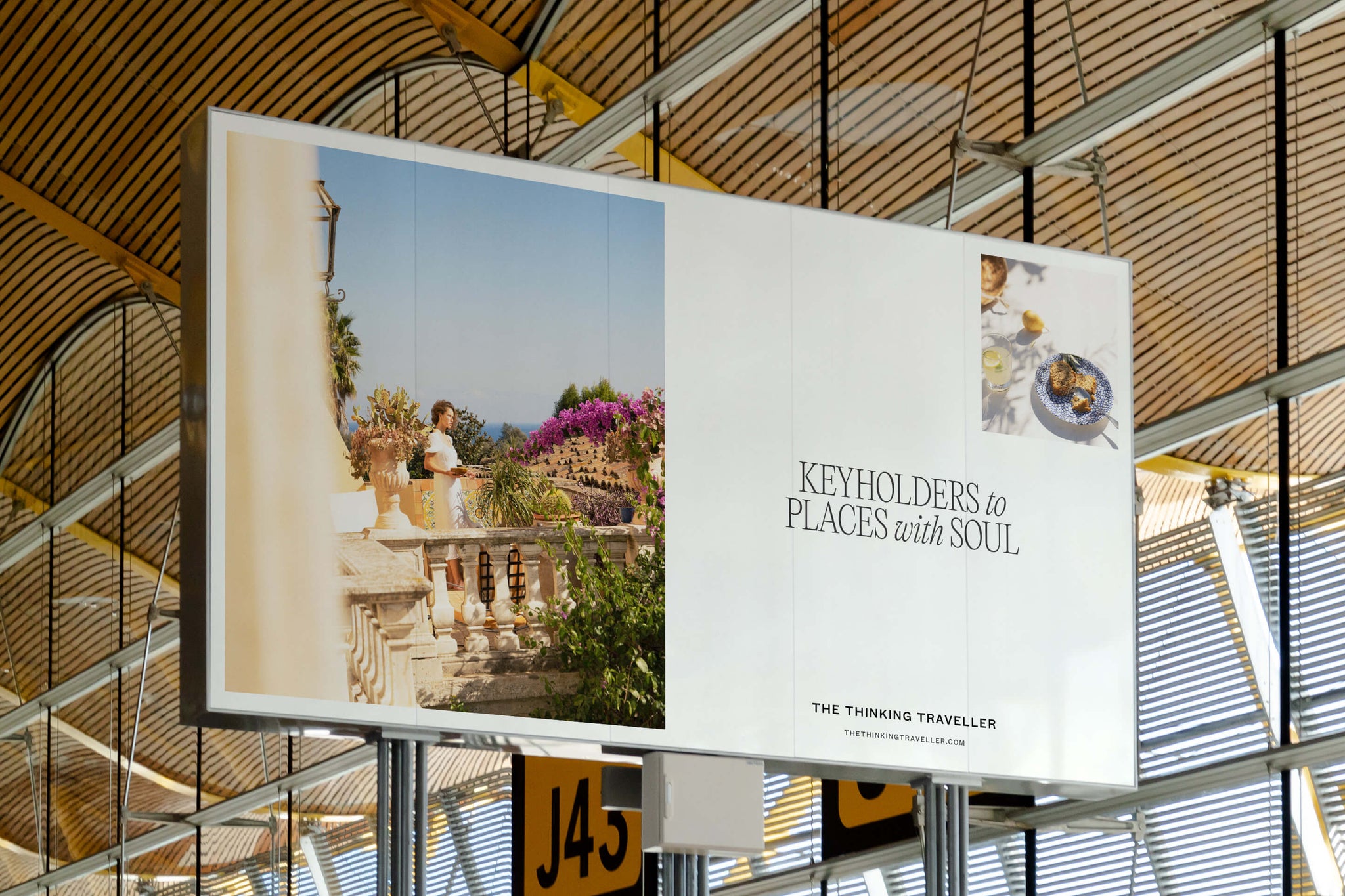
Depuis vingt ans, The Thinking Traveller rend les vacances en villa plus réfléchies.
Mais à mesure que le marché de la recherche de villas s'est développé, la marque s'est perdue dans un océan de piscines à débordement. Dans un marché de plus en plus générique et fonctionnel, pour inspirer le voyageur de luxe de demain, il lui fallait une marque qui prône l'originalité.
PARTAGER L'EXTRAORDINAIRE
Contrairement à ses concurrents, The Thinking Traveller propose ses maisons de caractère exclusivement par son intermédiaire. Grâce à leur connaissance approfondie de ces lieux, les équipes locales talentueuses peuvent créer des vacances uniques et sur mesure. Une identité de marque était donc nécessaire pour mettre en valeur cette expertise. Afin de repositionner The Thinking Traveller, non plus comme une agence de location de villas, mais comme un « détenteur de clés de lieux ayant une âme », nous avons commencé par décrire ces lieux exceptionnels dans un langage bien éloigné du jargon immobilier des « villas exclusives ».
PASSIONNÉ PAR LES LIAISONS HUMAINES
Mettre en œuvre une nouvelle image de marque tout en gérant une plateforme de réservation primée n'est pas chose aisée. Nous avons travaillé en Narrowcollaboration avec l'équipe de développement interne de l'entreprise pour l'aider à concrétiser cette nouvelle vision, tout en assurant une transition fluide et en maintenant le rythme soutenu des réservations pour la saison à venir.
DES LIEUX QUI TENENT À NOTRE CŒUR
L'histoire a été concrétisée par une direction artistique qui a dépassé les descriptions architecturales des villas pour évoquer l'âme de lieux empreints d'une âme. En collaboration avec la photographe Lavina Cernau, nous avons complété les images des villas de The Thinking Traveller par des interactions humaines, des reflets, des ombres et des détails singuliers. Lorsque la photographie était impraticable, nous avons créé des illustrations dans le style libre et intemporel d'un livre d'or.
Des tons méditerranéens, une typographie élégante et un logo plus intemporel et simplifié confèrent à The Thinking Traveller une image plus raffinée, plus confiante et plus proche du design et de la culture qui rendent ses destinations si uniques. Nous avons trouvé et exprimé notre différence – notre âme – dans une re de marque élégante et émouvante. Cette création se distingue sur un marché de plus en plus homogène et s'est avérée être la manière idéale de célébrer notre 20e anniversaire, tout en continuant d'inspirer le voyageur de luxe de demain. Elena Fotiadi, Responsable Marque et Partenariats, The Thinking Traveller